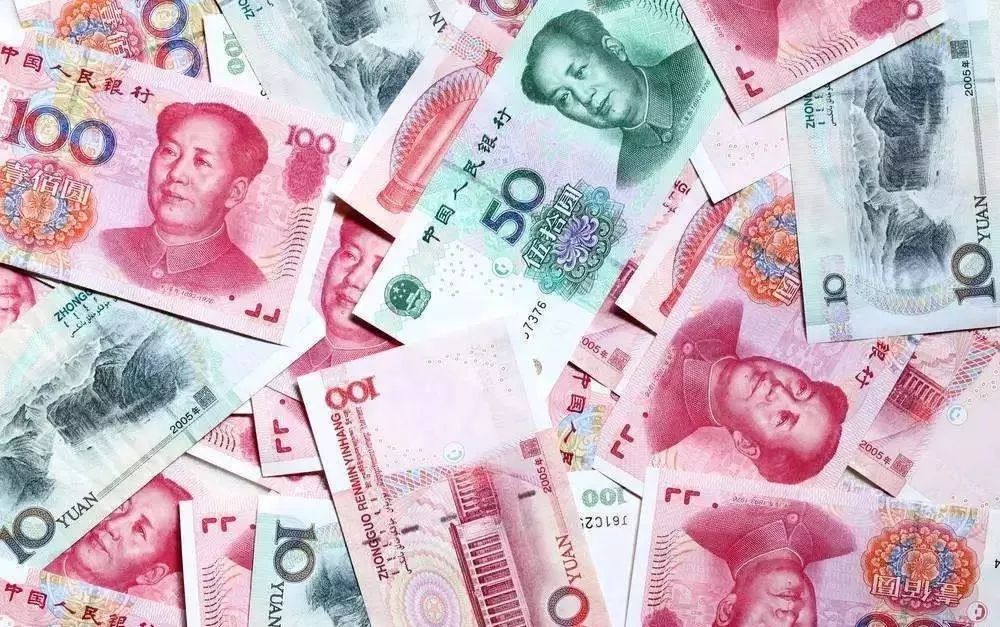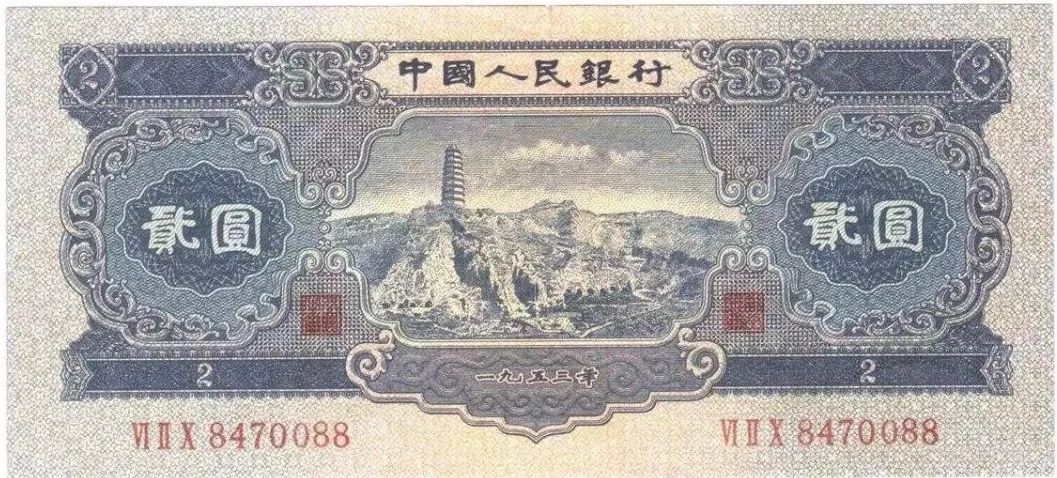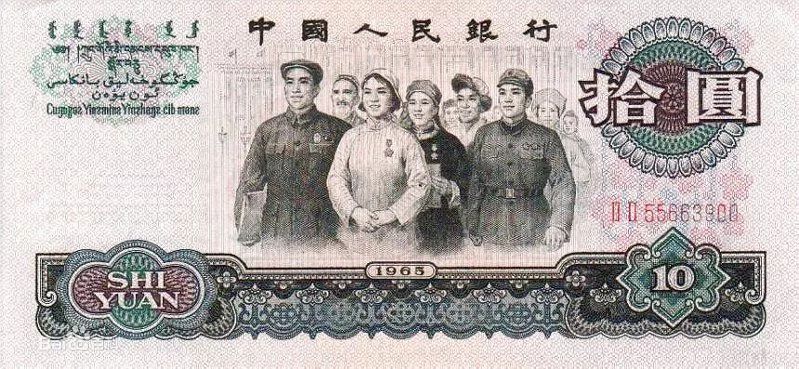
百元大钞背后的惊天秘密.....
今天的重点是:带大家一起了解从第一套人民币到目前流通的第五套人民币中的“中国人民银行”六个字的秘密。
人民币上的“中国人民银行”六个字,力足丰润,典雅和谐,刚柔并济,其书写风格很适合使用在钱币上。
那么问题来了~到底这些字体是哪里来的呢?
第一套人民币200元为例
第一套人民币上“中国人民银行”六个字为繁体字,柳体楷书,排列为自右向左,当时任华北人民政府主席董必武同志为该套人民币题写了“中国人民银行”行名。
第二套人民币至第五套人民币上“中国人民银行”六个字均为马文蔚所写。字体为张黑女,读作张(zhāng)黑(hè)女(rǔ),音(张贺汝),书法的一种碑体;这种字体首次出现在《张黑女墓志》上,《张黑女墓志》全称为《魏故南阳太守张玄墓志》,又称《张玄墓志》。(这都是知识点,知识点)
第二套人民币 2元为例
第二套人民币上“中国人民银行”六个字为繁体字,北魏碑体,排列为自左向右,1950年由当时在中国人民银行经济研究室任金融研究员的马文蔚所写。
第三套人民币 10元为例
这就是改革开放初期,大家称之为“大团结“的10元大钞。
第三套人民币上的面额汉字改用印刷宋体字,但“中国人民银行”六个字仍沿用,为繁体字,北魏碑体,排列为自左向右。
第四套人民币
第四套人民币,字体仍沿用马文蔚先生的“张黑女”碑体。但进行了改动。
一:面额汉字由印刷宋体字改成马文蔚的手迹
二:改繁体字为简体字。例如“中国人民银行”行名中的“国”和“银”两个字,六种主币面值的“圆” 字,都分别改成了“国”、“银”、“圆”。
三:改异体字为正体字。原来流通的人民币2元券、2角券、2分券的“贰”字中间的两横在上,现改成规范的正体字“贰”。
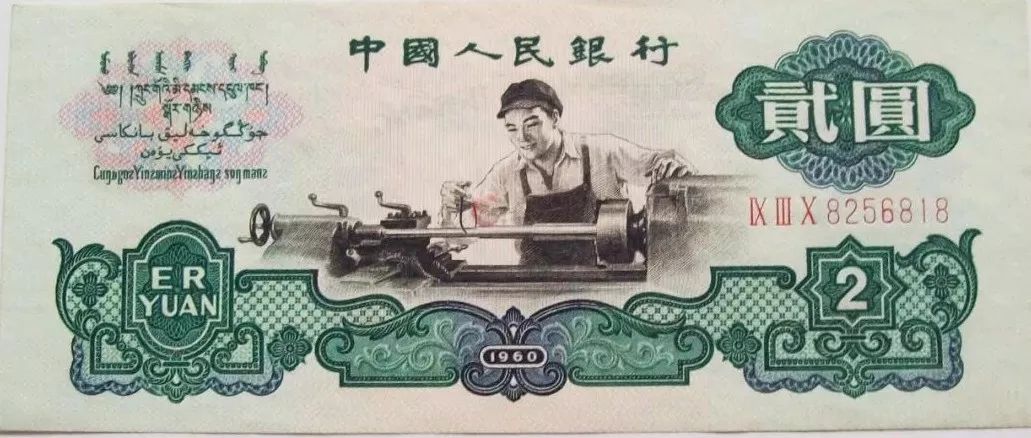
四:改旧字形为新字形。原来流通的人民币辅币1角、2角、5角券的“角”字写成“角”,中间的一竖不出头,现根据文化部、文改会 1965年联合颁布的印刷通用的汉字字形表,使用了新字形“角”,中间一竖出头。
现在隆重登场的是我们的第五套人民币~